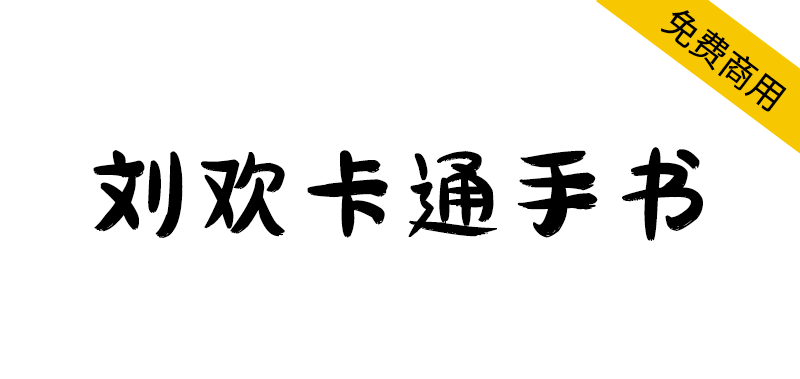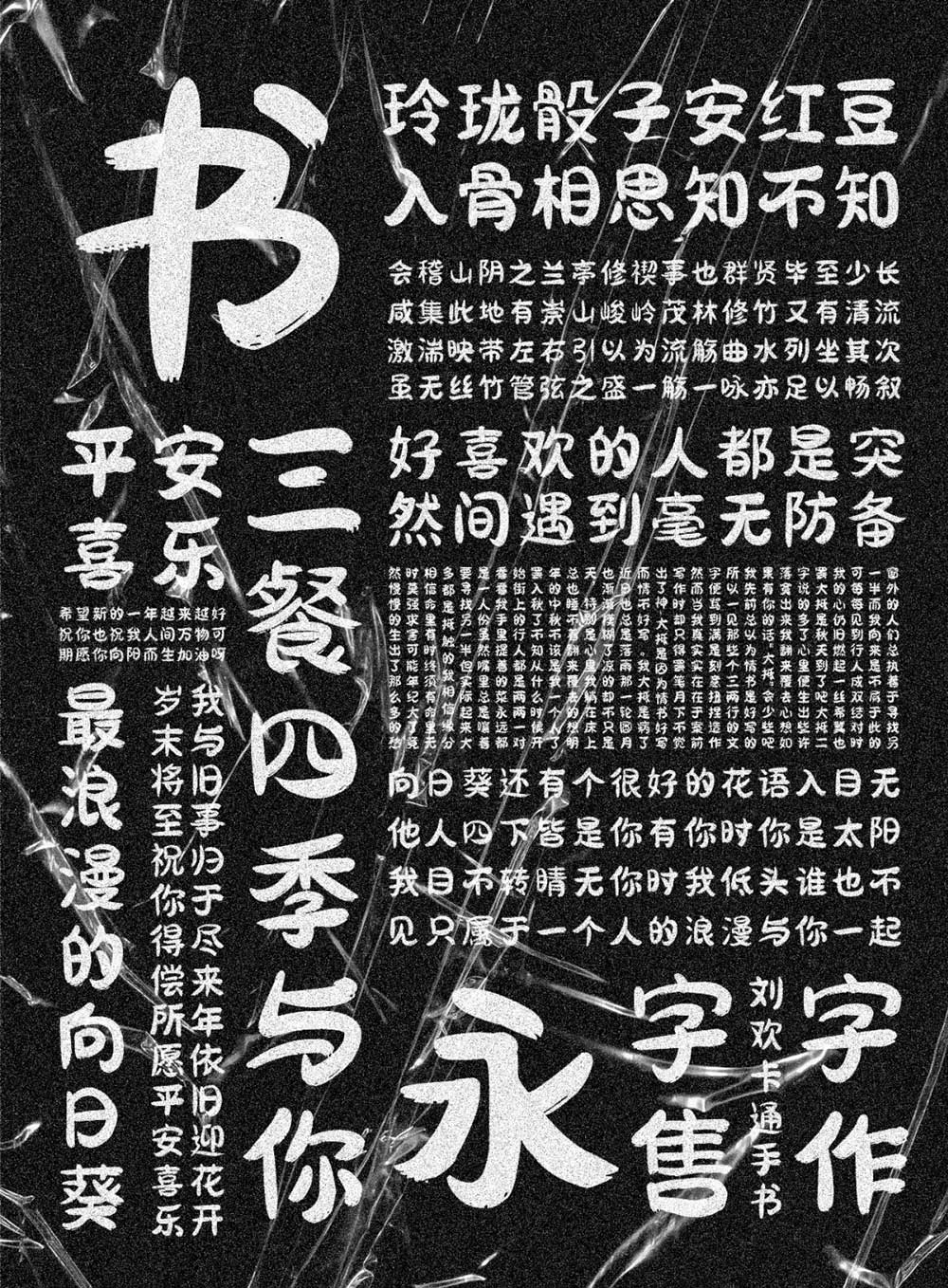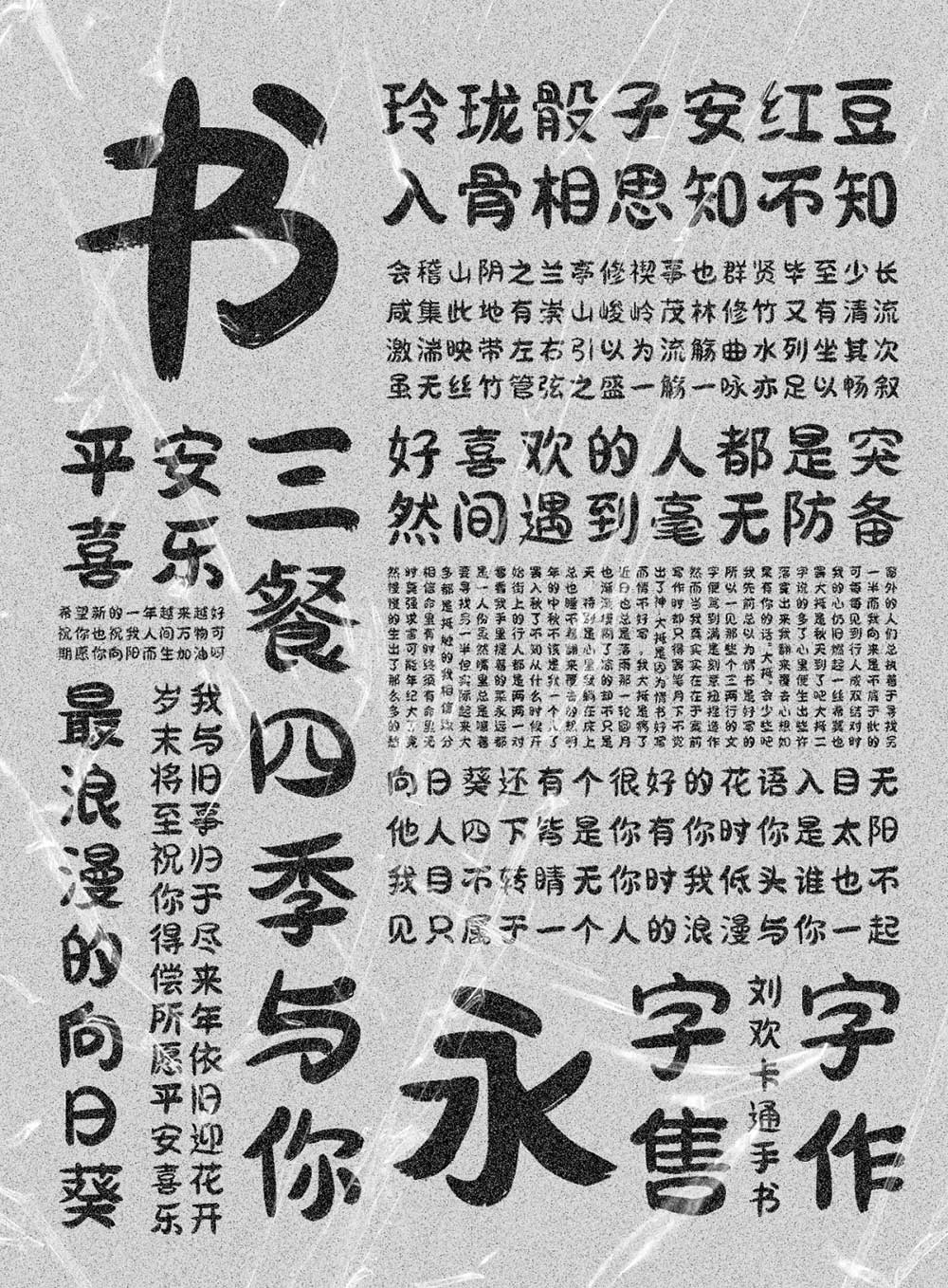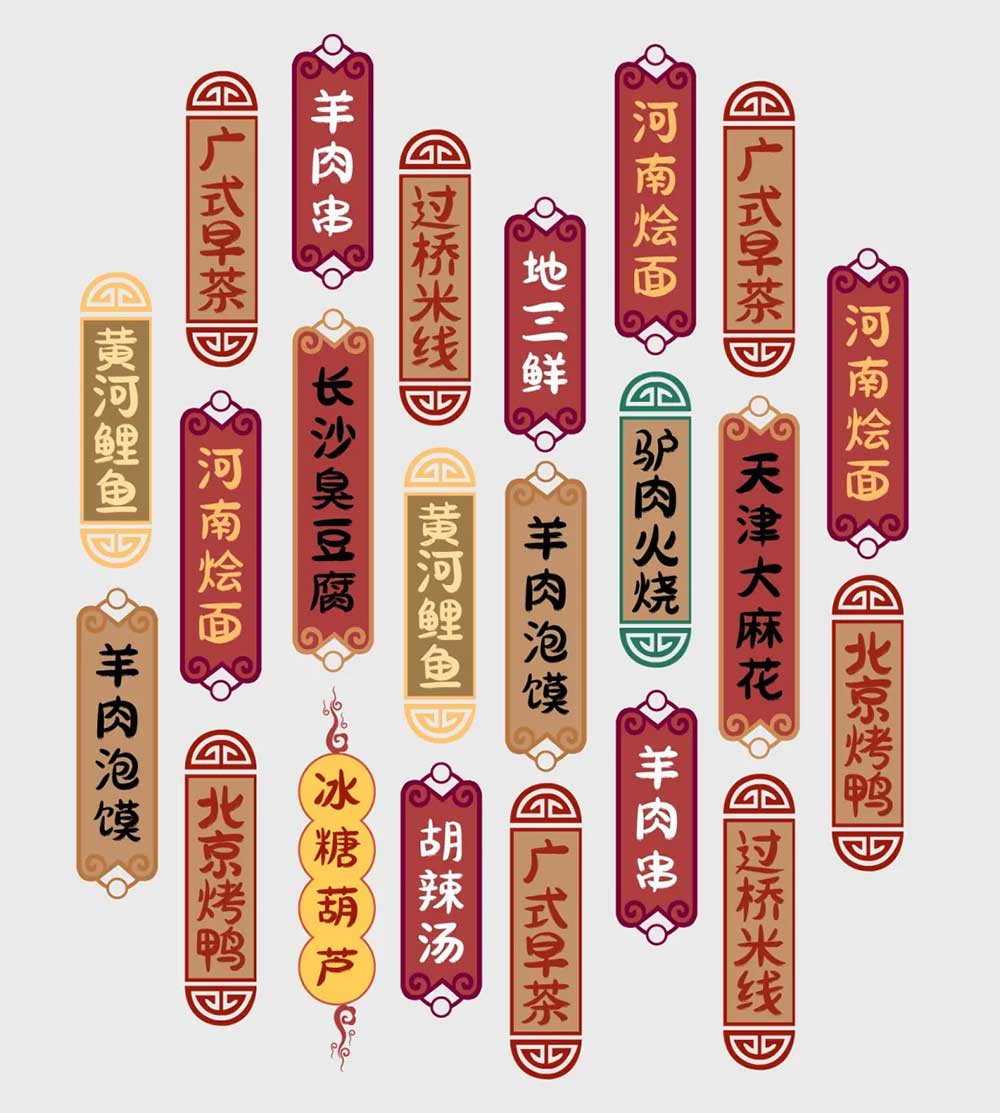
刘欢卡通手书是一款圆润卡通手写风格的标题字体,所有笔画以“圆润”为主,保留少量飞白,在屏幕上显示更佳。同时在线下使用也不缺失手写韵味。起名“卡通”字体,其实用作“标题字”也是OK的。该字库不限制使用场景,印刷书籍除外,不适合太小的字体展示。这套字库作者本人承诺永久免费商用!
作者/字体故事:2018年初,接触到字体设计,就被汉字的演变深深吸引,一向不爱写字的我才发现:原来汉字还可以这么美!
其实说起这套字库的创作初衷,是因为当时找的工作不合适然后回家了…